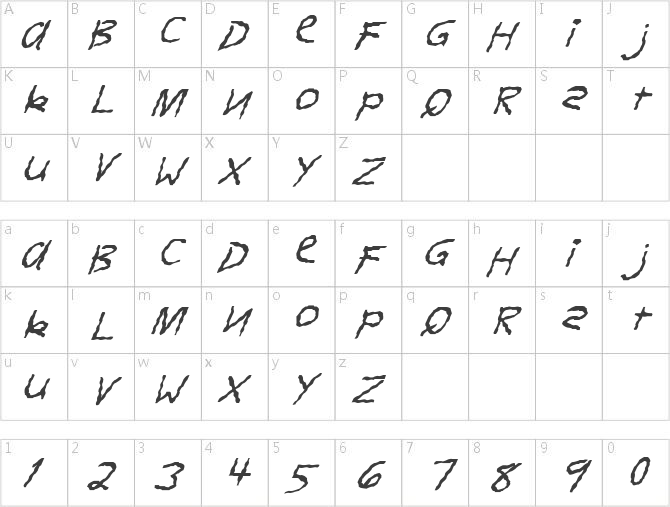
FZ HAND 11 WAVEY ITALIC
FZ HAND 11 WAVEY ITALIC介绍
FZ HAND 11 WAVEY ITALIC字体字库是一款让人赏心悦目、百看不厌的英文字体,适合各类广告和产品包装设计应用,字体大小0.08MB,格式为ttf字体,上传用户是白刃寒走得慢,作者/版权方为未知